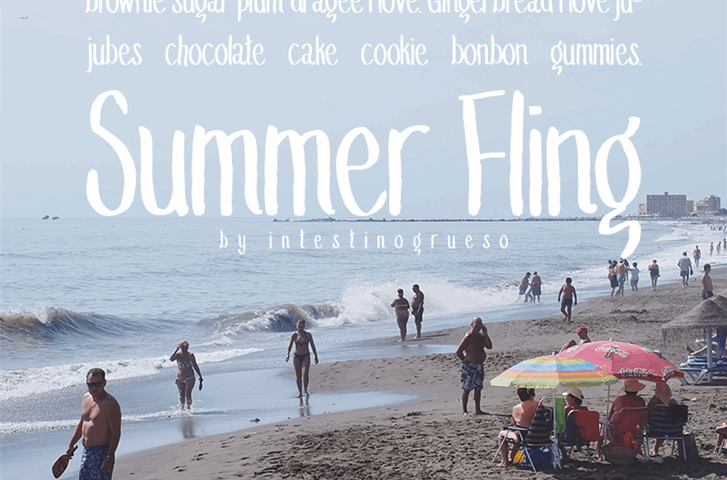
A Summer Fling Medium Font é perfeita para aqueles que procuram uma fuga do cotidiano, transformando suas criações digitais em obras de arte vibrantes e cheias de vida. Ideal para designers gráficos que desejam adicionar um toque de colorido a seus projetos, essa fonte brush captura o espírito da primavera com sua aparência leve, fluida e repleta de detalhes sutis. Seja você criando materiais para crianças ou produzindo elementos visuais para uma campanha publicitária, Summer Fling Medium Font oferece um conjunto amplo de opções para personalizar seu trabalho. Ideal tanto para uso em títulos quanto em pequenos textos, essa fonte traz alegria e energia ao design, transformando qualquer projeto em algo único e cheio de vida. Com uma paleta vibrante que inclui tons de vermelho, laranja, amarelo e dourado, Summer Fling Medium Font é perfeita para criar designs contemporâneos e vibrantes. Se você está à procura de uma fonte brush com um estilo único e moderno, essa fonte certamente se encaixa perfeitamente em seu portfólio.